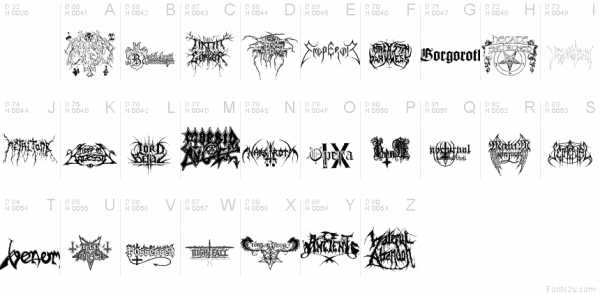
Шрифт Black Metal G , Дингбаты — Логотипы шрифты
Вы находитесь на странице шрифта Black Metal G. Он был создан дизайнером . Это бесплатный шрифт. Он может быть использован без каких-либо ограничений. Публикация шрифта на Fontzzz.com состоялась 09.02.2012 в 00:06. Он был помещен в категорию «Дингбаты — Логотипы«. Версия шрифта Black Metal G — «1.0 GERSAN BORGE triton company 2010». Вы можете скачать шрифт Black Metal G совершенно бесплатно и без регистрации, кликнув по ссылке «Скачать шрифт». Данный шрифт был сжат в ZIP-архив для вашего удобства. Архив содержит 1 файлов шрифтов.
Black Metal Logos шрифт